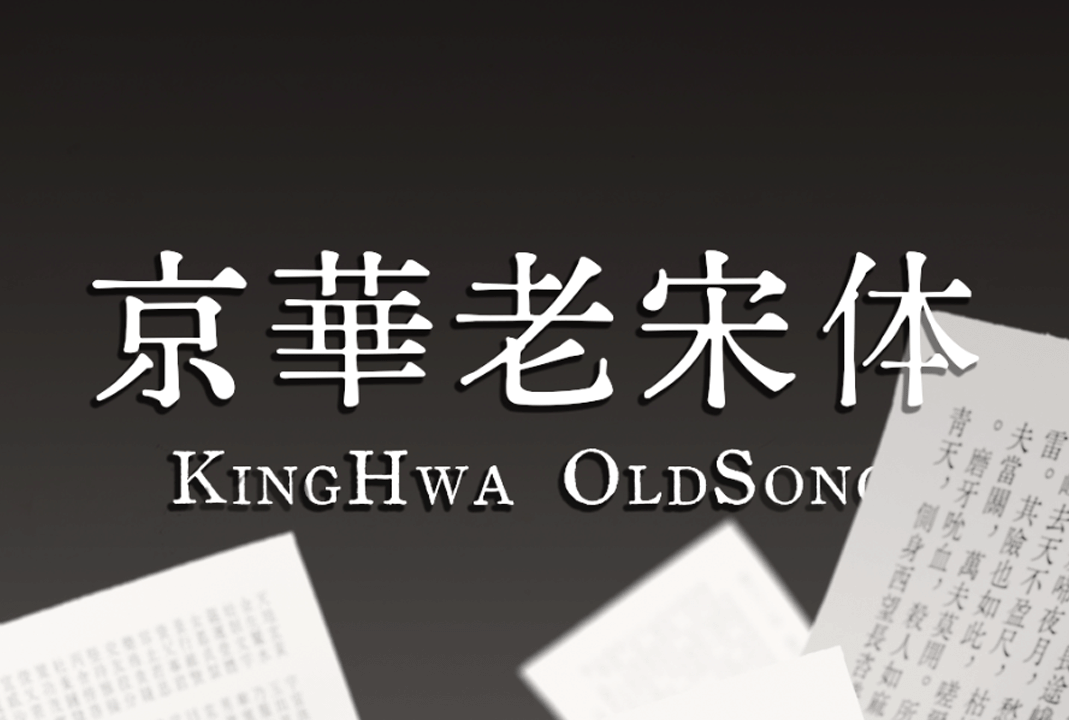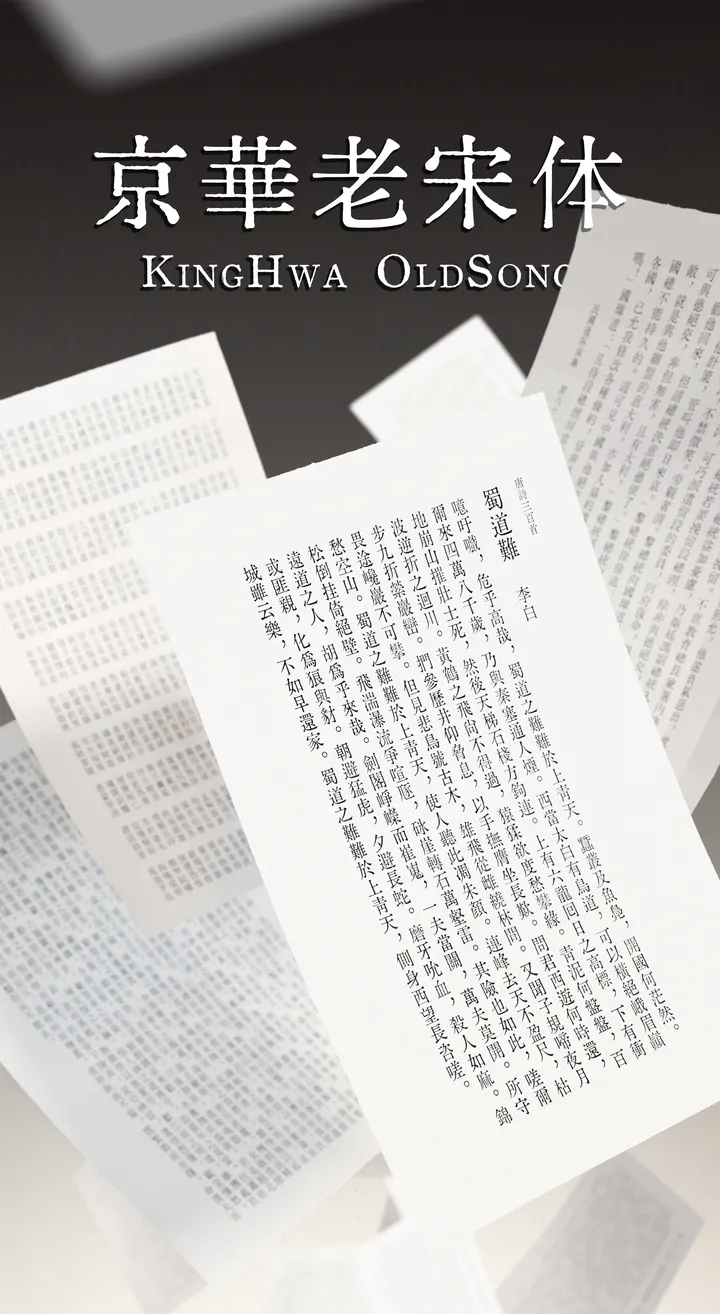
京華老宋体(KingHwa_OldSong)是由知乎网友(id:特里王)运用AI技术辅助生成的一款免费商用老宋体,风格来自于1961年北京新华字模厂改刻的老筑地体一一61-1体。
桃形点、鹅头勾和三角字肩,极具老宋体风味,较之如今最常使用之宋二体更加厚重圆润,基本还原六七十年代左右的印刷风貌。比之「汇文明朝体」时代距今更近,因此排版效果更加工整秀丽,少了一些破落、古拙的质感,多了一些标致、正规的气息。但在字形上又还没受到后来新字形的规范,正经的外表下暗藏一丝叛逆。